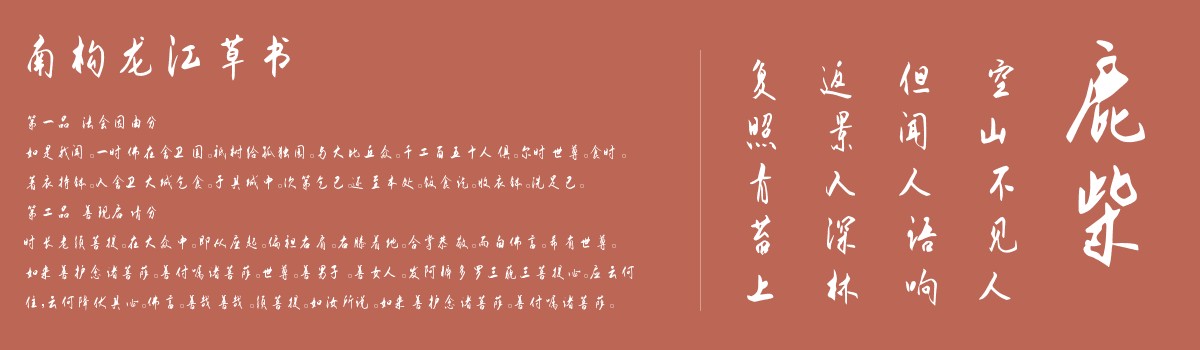
南构龙江草书
南构龙江草书是一款由字体家AI神笔造字生成的艺术字体,这款草书字体,线条如行云流水般连贯无滞,提按间自有自然的粗细变化——细处似游丝轻飏,带着书写时的灵动;粗处则含筋骨,透着沉稳的力量。偶有飞白,像枯叶在风中轻颤,添了几分苍劲的质感。整体气息柔中带刚,能感受到手腕婉转时的流畅,也能触到笔锋顿挫处的骨力,仿佛一笔呵成,却藏着收放自如的韵律,像听一曲抑扬顿挫的琴音,既有婉转的柔,又有铿锵的劲。适合用于一些广告标题、平面文案、海报标题、网页广告用字的编辑。